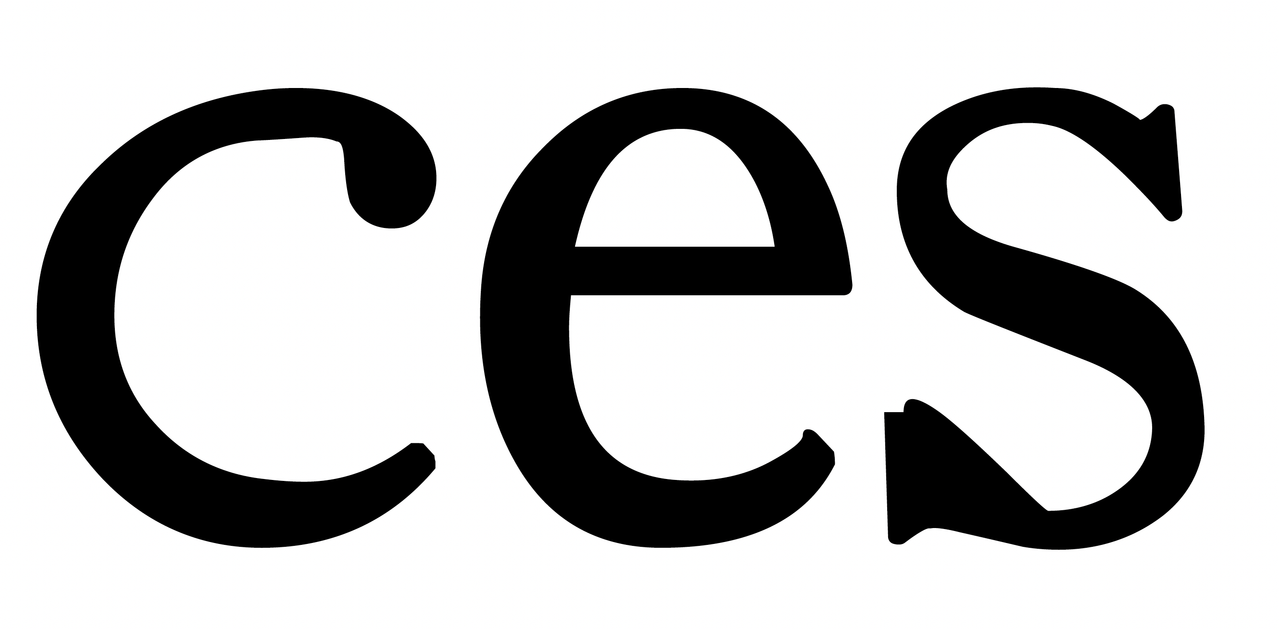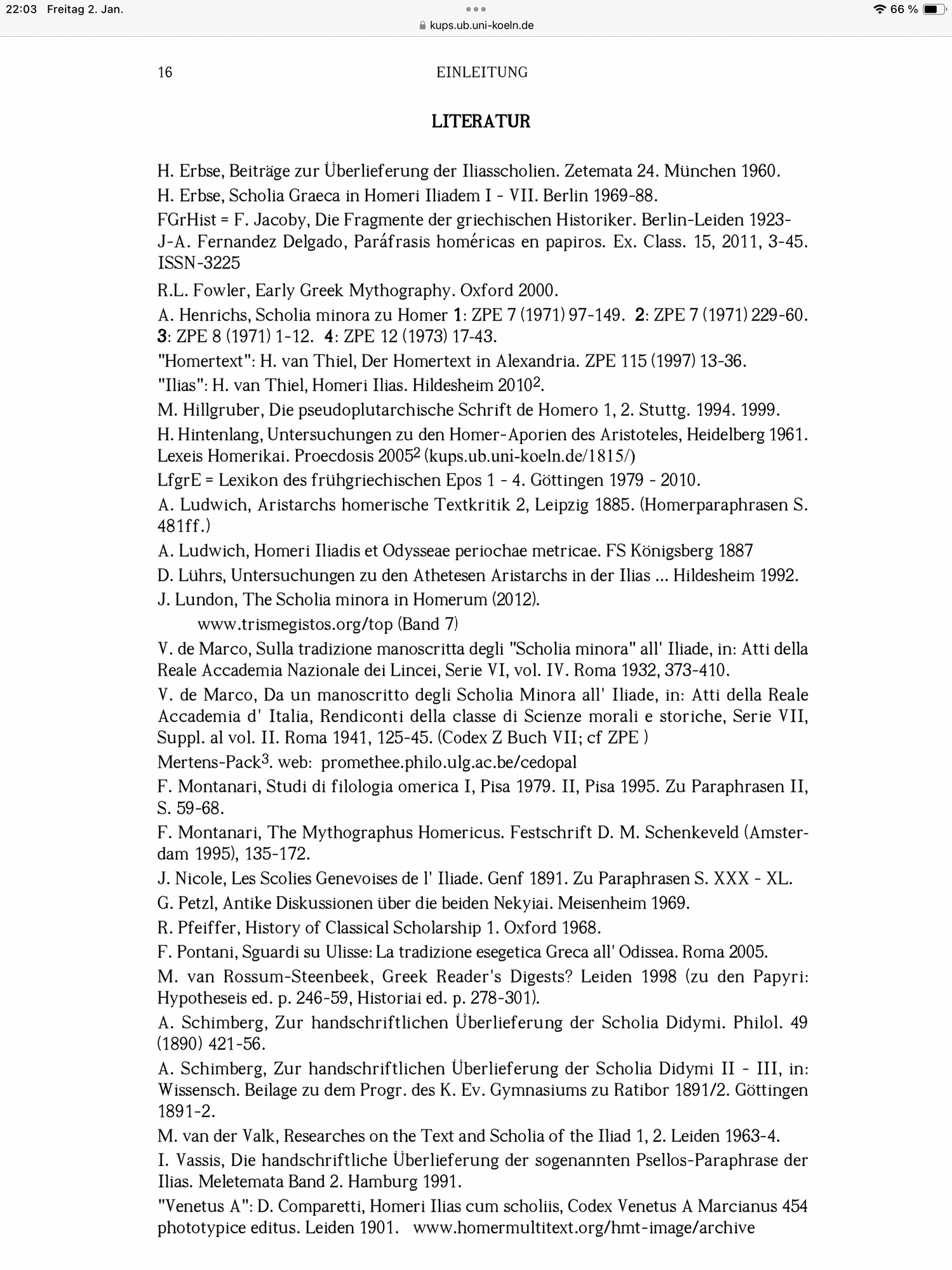
Welche Schriftart ist das? Kann mir jemand bitte weiterhelfen? (Scholia D in Iliadem)
Entnommen aus Scholia D in Iliadem. Proecdosis aucta et correctior 2014 … edita ab Helmut van Thiel (digitalisiert auch bei Wikipedia, „Helmut van Thiel“, dort unter Weblinks)
Im PDF nennt sie sich Homeric. Irgendwas aus der LaTeX-Welt?
@Ralf Herrmann Nur der Neugierde halber : Was deutet hier für Dich auf LaTeX hin?
Für mich würde darauf hindeuten, dass sie nicht aufzufinden ist, so wie viele andere Latex-Fonts auch.
Das pdf wurde aber in Word am Mac erstellt, da würde ich spontan nicht von einem Latex-Font ausgehen.
Beim Fehler im s und den vielen Unsauberkeiten frage ich mich aber, was dem armen Font denn passiert ist …
Ich kann da aus der LaTeX-Welt tatsächlich auch sehr üble Geschichten berichten. Die für LaTeX so übliche Computer Modern sieht in manchen Übersetzungen mit pdfLaTeX furchtbar pixelig aus und ich sehr schlecht zugerichtet. Mit LuaLaTeX passiert das komischerweise nicht. Ich weiß nicht, warum.
Vielleicht sind diese Fehler tatsächlich beim Portieren eines LaTeX-Fonts nach Mac entstanden?
Was meinst du mit "portieren"? Sind das nicht einfach ttf oder otf?
Wenn Du LuaLaTeX nimmst, kannst Du ttf oder otf verwenden. Mit »normalem« LaTeX geht das nicht so ohne Weiteres. Da werden die Fonts als proprietäre Pakete eingebunden. Ich habe den Umgang mit otf- und ttf-Files erst gelernt, als ich anfing, mich mit XeLaTeX und LuaLaTeX zu beschäftigen.
Ich vermute, dass Homeric der Font ist, der für das polytonische Griechisch genutzt wurde. Da das ein Postscript-Font ist, kann der aus einem der damaligen Hilfsprogrammen stammen, die genutzt wurden, um in der Vor-Unicode-Zeit polytonisches Griechisch zu schreiben.
Die lateinischen Glyphen werden eher der timesnewromanpsmt (winansi-Kodierung) entstammen.
Wofür brauchst Du die Info? Es gibt viel bessere Schriften, als die, die in den PDF verwendet wurden, auch kostenfreie.
Ich hätte diesen Schrifttyp, der so ungemein nüchtern ist u. schmucklos daherkommt, gerne für ein Dissertationsvorhaben in den Geisteswissenschaften verwendet. Eine nahe an dem obigen Bild liegende Schrift schien mir Cambria zu sein. Aber ich bin Laie, u. für einen Hinweis deshalb dankbar.
Wie der Font in diesem Werk heißt ist egal, weil er (wie erwähnt) so gravierende Mängel hat, daß er für eine Verwendung nimmer infragekommt. Aber es gibt gute Möglichkeiten, nach solide gemachten Fonts ähnlicher Art zu suchen:
Brauchst Du eine bestimmte Zeichenunterstützung wie polytonisches Griechisch oder andere spezielle Zeichen?
Ich empfehle Dir, keinen extra Zeichensatz für verschiedene Sprachen zu nutzen, sondern eine Schriftart für alles. Dies lässt eine Seite sehr viel ausgewogener erscheinen, da die Künstler darauf achten, dass über die verschiedenen Schriftsysteme auch all die kleinen Details zueinander passen.